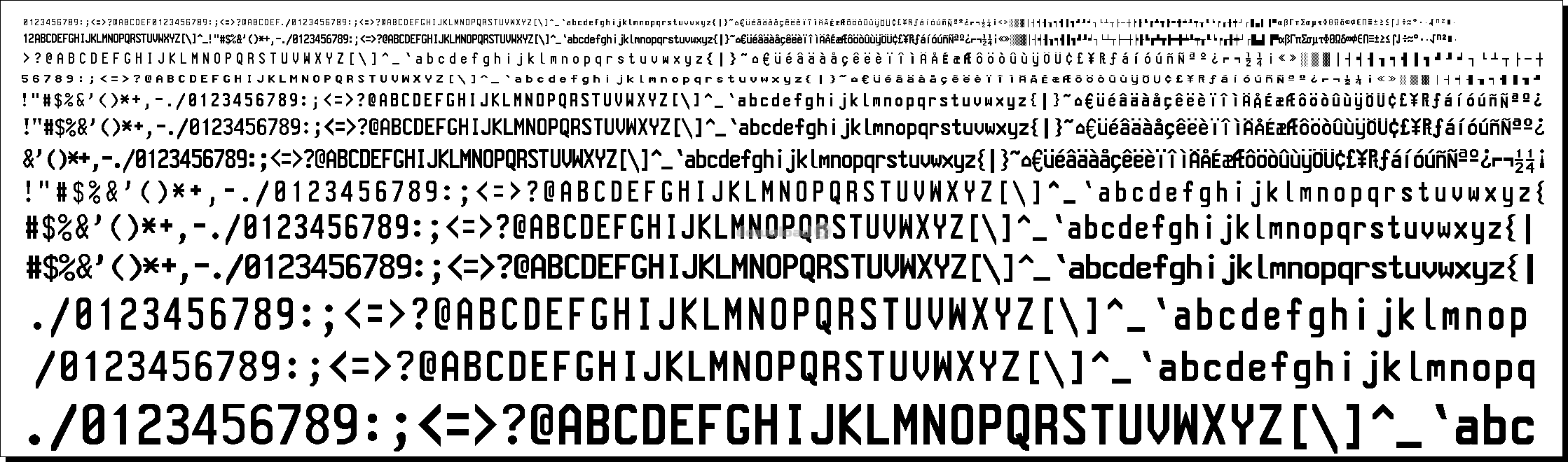
HVLJFont - Soft Fonts for Laser Printers 1.0
"Hi-Visibility Font for HP Laserjet printers"
Le paquet HVLJFont fournit des polices téléchargeables PCL "soft" pour une utilisation avec les imprimantes HP LaserJet compatible. Les polices peuvent être utilisées avec MS-DOS, les programmes de terminaux de Windows, Unix, Linux, Macintosh et le système AS/400 dIBM.Ils sont particulièrement utiles si vous avez une imprimante laser qui ne fournit pas les polices à pas fixe qui sont évolutives, ou suffisamment lisible.
Ces hautement lisibilité, les polices à pas fixe sont basés sur la conception HVFont ProCon.
Les tailles vont de un 50cpi minuscule, 3pts, jusquà un 8.33cpi grand, 17pts.
Les tailles de 30cpi à 15cpi sont les plus utiles que quelques imprimantes produisent texte lisible à ces dimensions avec leurs polices natives.